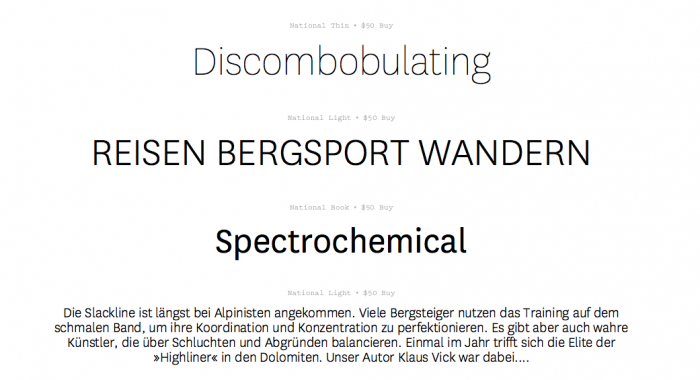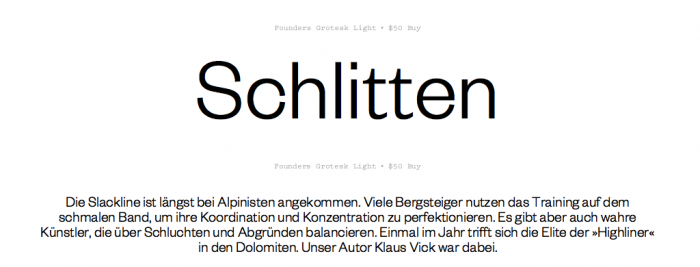
Alternative zu Founders Grotesk / National
Im Rahmen meiner Bachelor-Arbeit entwickle ich ein neues Corporate Design.
Ich bin total begeistert von der National und Founders Grotesk (von Chris Sowersby),
da sie sehr charakteristisch auf Plakaten wirken, als Fließtext funktionieren und gut
zu meinen Anmutungs-Kriterien passen. Leider wurden von Klim noch keine passenden
Webfonts entwickelt und via Hinting ist es wohl sehr teuer und aufwendig.
Nun meine Frage: Könntet ihr mir Alternativen hierzu empfehlen, die den Schriften sehr
nahe kommen und die es bereits als Webfont gibt?
(Die FF Bau und FF Basic Gothic kommen für mich eher nicht in Frage)
National:
fände ich die Corporate S BQ Medium eine sehr gute Alternative. Eventuell kommt auch die Guanabara in Frage.
Allerdings habe ich da ein bisschen Bedenken bei den Bold-Schnitten, ob die Lesbarkeit auf Plakaten nicht zu sehr
beeinträchtigt wird.
Post Grotesk ist doch auch was (Hochwertiges). Und laut vllg.com gibt es die auch als Webfont: